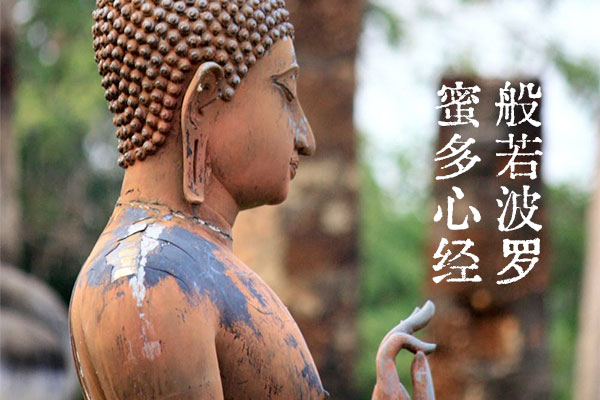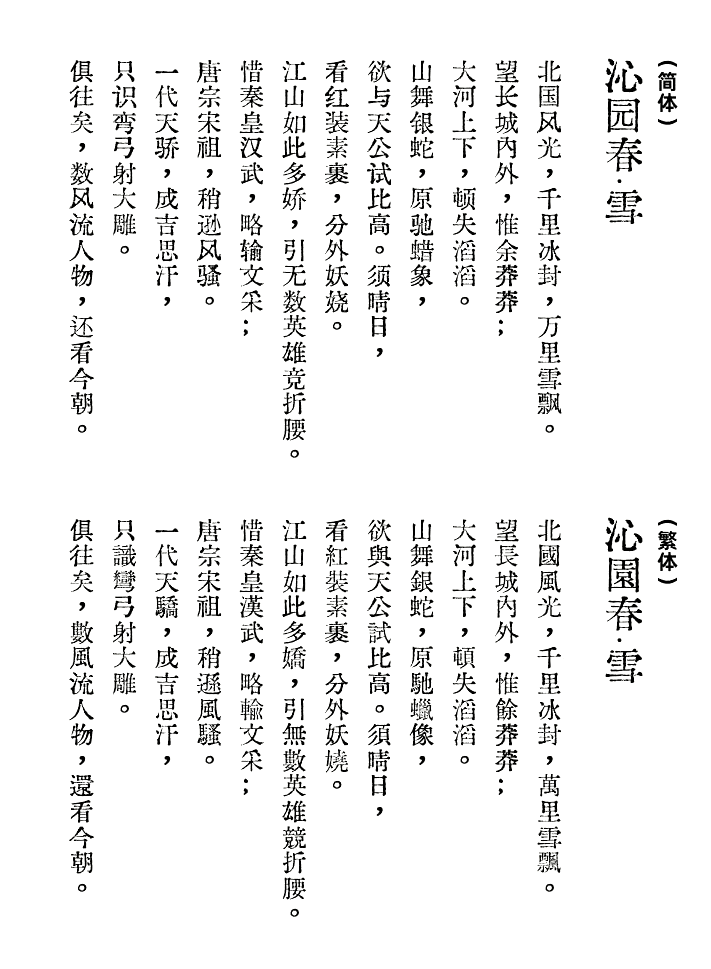
汇文明朝体
汇文明朝体是百度旧字形吧网友天王帝廷发布的一款中文字体,始于2019年1月,以《文汇报》的《汉字简化方案草案》为起点,收集、扫描历史文献资料后整理而成。其字形主要源自五六十年代的汉字改革文件,简体字还原简化前的书籍印刷体,繁体字和传承字则恢复民国至共和国初期的字形,风格为原味的旧铅字印刷。
该字体涵盖了大陆「GB2312」标准的6763字、台湾「常用国字标准字体表」以及日本常用、人名用、表外汉字表的新字体,适用于日常使用。此外,该字体还以Oradano明朝为原型,逐步替换字形,形成了汇文明朝体。它被授权用于印刷、显示、嵌入电子文档和设备,可以自由转发,也可以作为更大规模软件套件的一部分销售(不单独出售字体文件),并可用于新字体的开发。
汇文明朝体效果预览
汇文明朝体字体效果预览